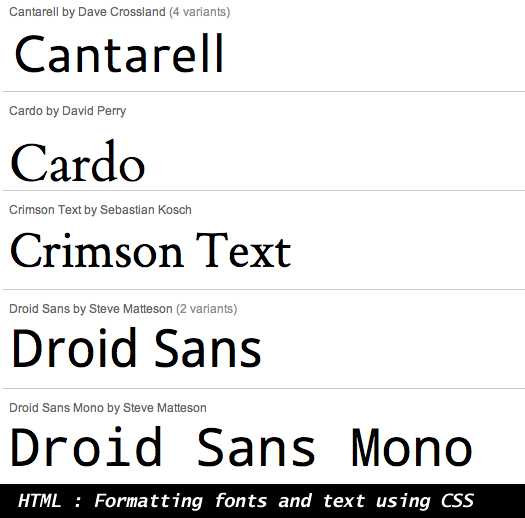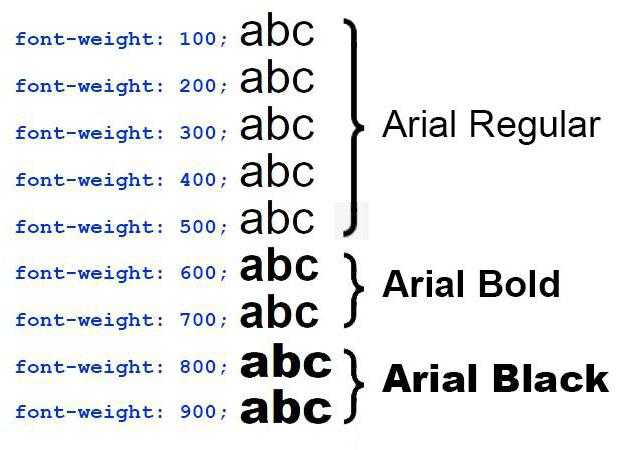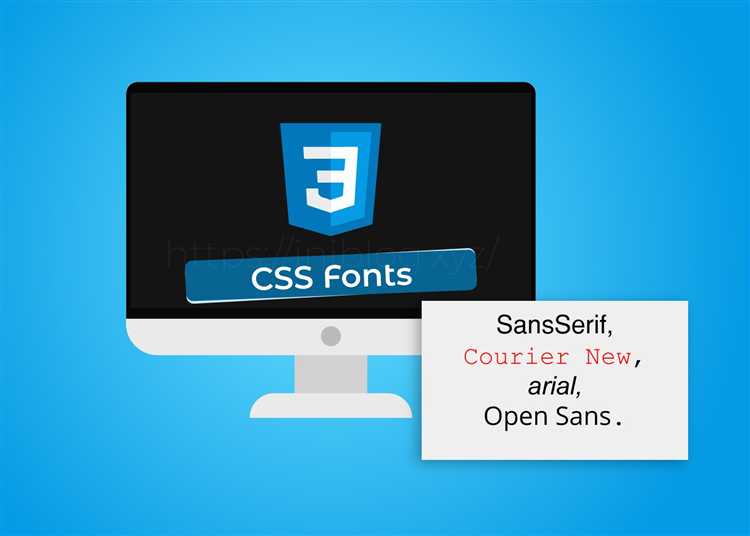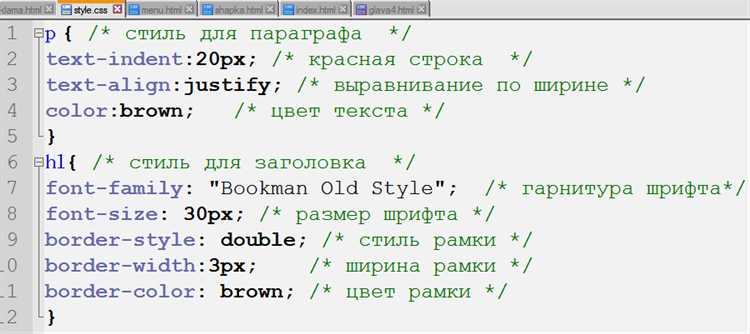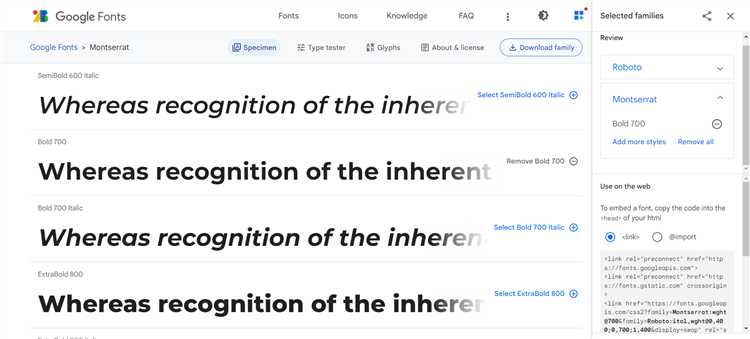
Веб-дизайн и разработка не обходятся без работы с шрифтами, так как правильно подобранный шрифт значительно улучшает восприятие контента. CSS предоставляет широкие возможности для настройки шрифтов на веб-странице, включая их стиль, размер и тип. Выбор шрифта оказывает прямое влияние на читаемость, визуальную гармонию и даже SEO-позиции сайта.
Типы шрифтов в CSS можно разделить на несколько категорий: системные шрифты, веб-шрифты и шрифты, загружаемые с внешних ресурсов. Системные шрифты — это те, которые уже установлены на устройстве пользователя, такие как Arial, Times New Roman или Courier. Использование таких шрифтов имеет свои плюсы: они быстро загружаются, не требуют дополнительного трафика, но могут не подходить для всех типов дизайна.
Для более гибкой настройки дизайна часто применяются веб-шрифты, которые загружаются с серверов. Эти шрифты позволяют задать уникальный стиль, который будет одинаково отображаться на всех устройствах, независимо от того, установлен ли этот шрифт у пользователя. Один из популярных способов подключить веб-шрифт – использовать сервисы, такие как Google Fonts или Adobe Fonts. При этом важно учитывать, что чрезмерное использование внешних шрифтов может замедлить загрузку страницы.
Особое внимание стоит уделить выбору шрифта для текста, который будет прочитан на разных экранах. Шрифты для мобильных устройств должны быть легкими для восприятия, поэтому рекомендуется использовать более четкие и читаемые варианты, такие как sans-serif шрифты, в то время как для печатных изданий можно использовать более декоративные serif-шрифты. Важно помнить, что использование слишком мелких шрифтов на мобильных устройствах может привести к ухудшению UX.
Также, не стоит забывать о принципах доступности, где правильный выбор шрифта и его размера позволяет сделать контент доступным для людей с ограниченными возможностями. Рекомендуется использовать контрастные комбинации цветов, чтобы улучшить читаемость текста на разных фонах.
Шрифты в CSS: их виды и особенности использования
Шрифты в CSS играют ключевую роль в создании визуального восприятия контента на веб-страницах. Они влияют на читабельность, структуру и общую эстетику сайта. CSS предоставляет несколько способов работы с шрифтами, а также различные типы шрифтов, которые можно использовать для достижения нужного эффекта.
В CSS шрифты можно разделить на три основные категории: системные шрифты, веб-шрифты и пользовательские шрифты. Каждый тип имеет свои особенности и подходит для разных задач.
Системные шрифты – это шрифты, уже установленные на большинстве операционных систем. Они обеспечивают быструю загрузку, так как не требуют дополнительных запросов к серверу. Примеры системных шрифтов: Arial, Times New Roman, Courier New. Важно помнить, что каждый пользователь может иметь разные шрифты в зависимости от операционной системы, поэтому для гарантированного отображения текста рекомендуется указывать несколько вариантов шрифтов в списке (fallback). Например: font-family: Arial, Helvetica, sans-serif;
Веб-шрифты загружаются с внешних серверов через сервисы, такие как Google Fonts или Adobe Fonts. Эти шрифты обеспечивают более широкий выбор, включая уникальные типографические решения. Для использования веб-шрифтов нужно указать их через @font-face или подключить через ссылку. Пример подключения с Google Fonts: @import url('https://fonts.googleapis.com/css2?family=Roboto&display=swap');
. Веб-шрифты увеличивают время загрузки страницы, но дают больше гибкости в дизайне.
Пользовательские шрифты – это шрифты, которые могут быть загружены с сервера вашего сайта с помощью @font-face. Это дает возможность использовать любые шрифты, даже если они не доступны через стандартные веб-сервисы. Пример использования: @font-face { font-family: 'MyCustomFont'; src: url('path/to/font.woff2'); }
. Такой подход позволяет добиться максимальной индивидуализации сайта, но требует внимательности к производительности.
При выборе шрифта важно учитывать его назначение. Для текстов, где важна читаемость (например, статьи, блоги), стоит выбирать шрифты с хорошей контрастностью и нейтральным стилем, такие как Roboto, Open Sans или Georgia. Для заголовков и акцентов можно использовать более выразительные шрифты, но важно соблюдать баланс, чтобы шрифт не загромождал восприятие. Также следует помнить, что шрифт должен соответствовать стилю сайта, будь то минимализм, классика или современный стиль.
Не забывайте о доступности: шрифты должны быть четкими на всех устройствах, а контрастность текста должна быть достаточной для удобства чтения. Для улучшения читабельности также полезно регулировать межстрочный интервал (line-height) и размер шрифта в зависимости от типа контента.
Важно помнить, что использование нестандартных шрифтов может повлиять на производительность сайта. Загрузка дополнительных файлов увеличивает время загрузки страницы, особенно если используются несколько шрифтов или весомые файлы. Для оптимизации стоит выбирать шрифты с минимальным весом и использовать only-latin или subset для языков, в которых не требуется весь набор символов.
Что такое веб-шрифты и как их использовать в CSS?
Веб-шрифты — это шрифты, которые можно загрузить с серверов через интернет и использовать на веб-страницах. Примеры таких сервисов — Google Fonts и Adobe Fonts. Для использования веб-шрифта в CSS необходимо добавить специальный код в HTML-документ, который подключает шрифт с внешнего источника. После этого в CSS можно указать шрифт через свойство font-family. Это дает возможность использовать стильный текст, не завися от шрифтов, установленных на устройстве пользователя.